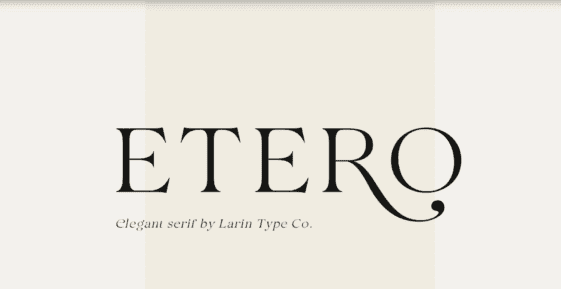
Название: Etero Font (2021)
Etero - это современный и элегантный шрифт с засечками, который будет потрясающе смотреться в логотипах, фирменной продукции, свадебных приглашениях, визитных карточках, упаковке, заголовках и многом другом. Читабельный и легко узнаваемый, он сделает ваш проект элегантным и уникальным, а наклонный стиль добавит динамики вашему дизайну.
Название: Etero Font (2021)
Etero - это современный и элегантный шрифт с засечками, который будет потрясающе смотреться в логотипах, фирменной продукции, свадебных приглашениях, визитных карточках, упаковке, заголовках и многом другом. Читабельный и легко узнаваемый, он сделает ваш проект элегантным и уникальным, а наклонный стиль добавит динамики вашему дизайну.